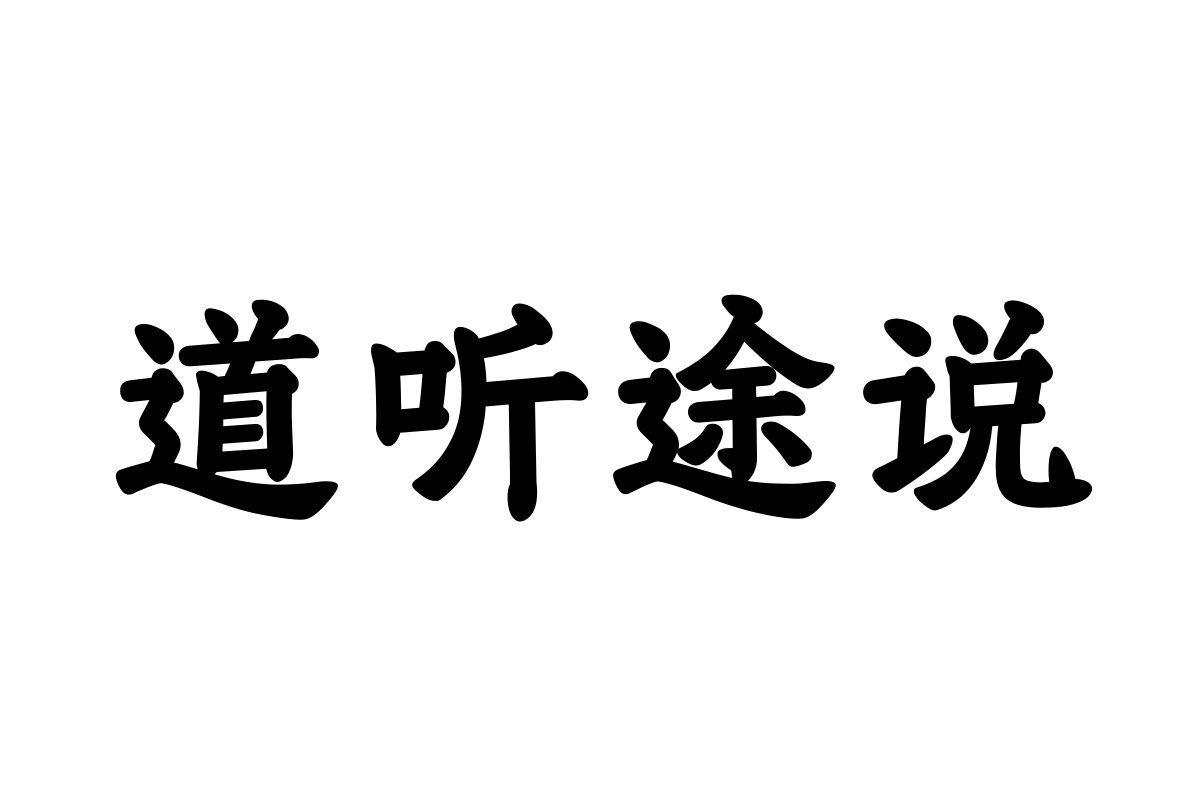
汉仪花冠字体是一款具有独特美感的中文字体,由汉仪字库设计。这款字体线条流畅自然,字形优美,适合用于各类文字设计,如标题、正文、广告等。其特点如下:
1. 字形优美:汉仪花冠字体线条流畅自然,字形优美,给人以优雅、高贵的感觉。
2. 风格独特:汉仪花冠字体采用了独特的艺术手法,使得每个字符都富有个性,形成了独特的艺术风格。
3. 适用范围广泛:汉仪花冠字体适用于各种文字设计,无论是标题、正文还是广告,都能展现出其独特的魅力。